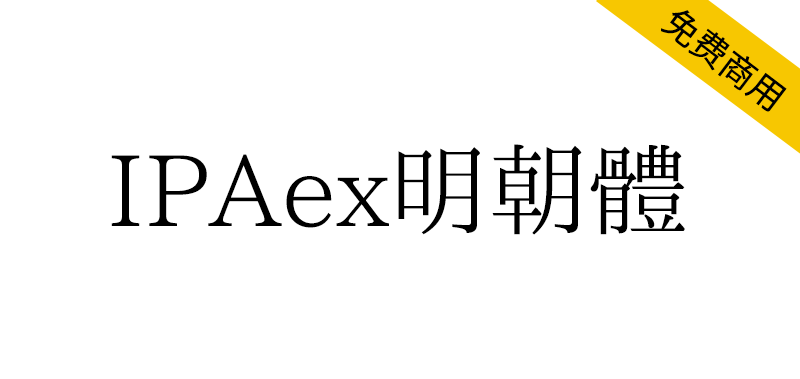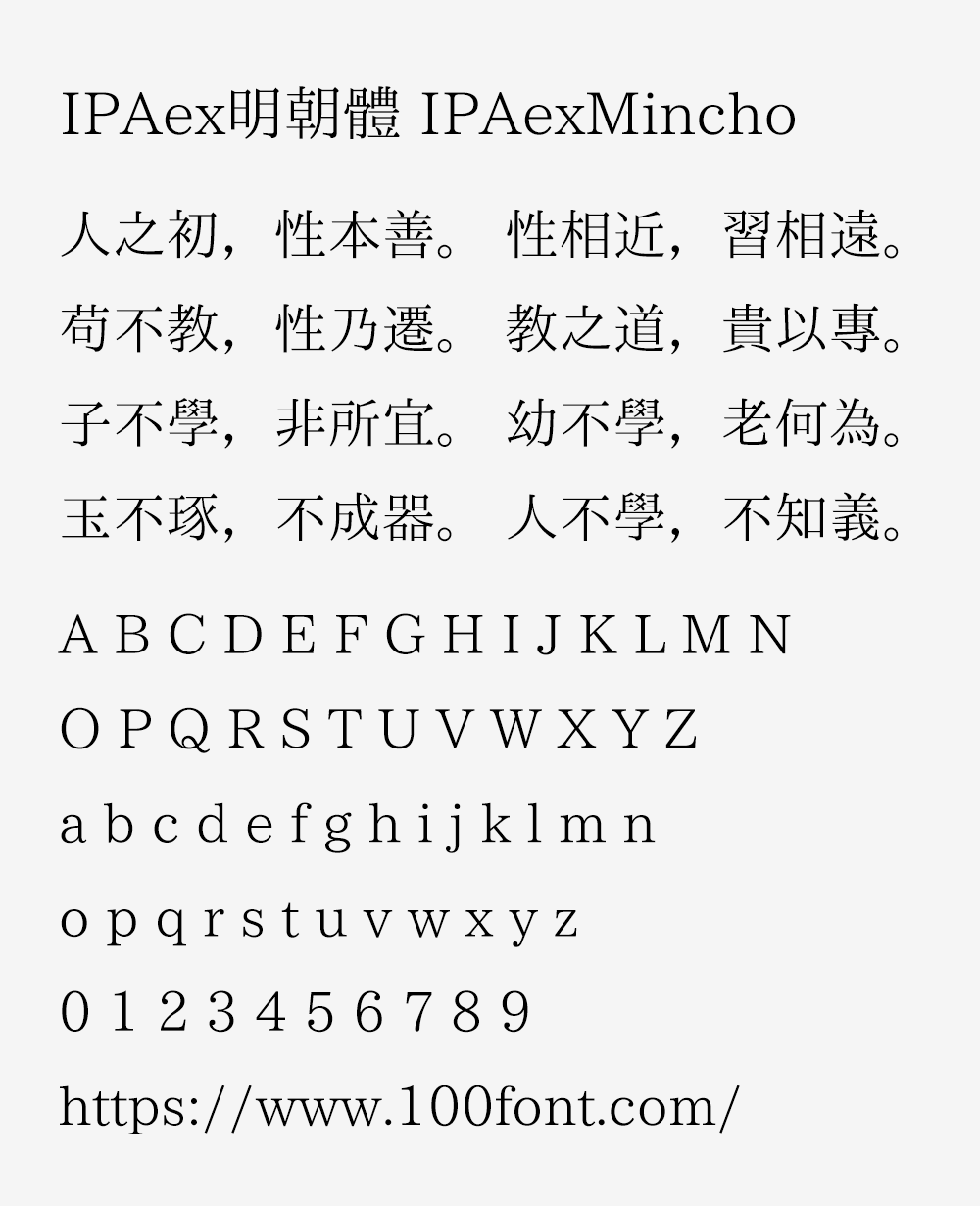
【IPAex明朝体】日本字体的标准实现文档宋体字体
揭秘日本文档背后的标准字体:IPAex明朝体如何革新日文排版体验?这款巧妙融合和文固定宽度与欧文变宽度设计的字体,以开源授权形式打破商业壁垒,获得OSI认证。无论是专业出版还是日常办公,它都能为你的日文文档注入专业品质,同时提供前所未有的使用自由。
【IPAex明朝体】日本字体的标准实现文档宋体字体
自2003年底以来,IPA一直在发布IPA拥有所有权利的“ IPA字体*”。 2010年2月,将IPAEX字体(IPAEX明朝体,IPAEX 黑体两种字体)添加到阵容中,这是日本字体的标准实现文档字体。 “ IPAEX字体”是一种旨在提高日本文档的便利性的字体,日本文字(例如Kana和Kanji)以固定宽度实现,欧洲文字是可变宽度以匹配文字宽度的可变宽度。 如果您想与过去的系统兼容,还可以使用四种类型的字体:“ IPA明朝体”和“ IPA黑体”,它们的欧洲和日本文字都具有固定宽度,以及“ IPA P 明朝体”和“ IPA P 黑体”,它们的欧洲和日本文字具有可变宽度。 “ IPAEX字体(VER.001及以后)”和“ IPA字体(Ver.003及以后)”是获得许可的“ IPA字体许可证”,这与国际实践作为开源许可证是一致的。该许可证在2009年4月1日获得OSI认证为“开源计划”(OSI)“开源定义(OSD)”。 *IPA字体是IPA的注册商标。
IPAでは2003年末よりIPAが全権利を所有する「IPAフォント*」を公開して参りました。2010年2月には、ドキュメント用日本語フォントの標準的な実装を行った「IPAexフォント(IPAex明朝、IPAexゴシックの2フォント)」をラインナップに加えました。  「IPAexフォント」は、和文文字(仮名や漢字など)は固定幅、欧文文字は文字幅に合わせた変動幅を基本とした実装を行い、日本語文書作成の利便性の向上を目指したフォントです。  なお、過去のシステムとの互換性を求める場合には、欧文文字、和文文字ともに固定幅の「IPA明朝」と「IPAゴシック」、欧文文字、和文文字ともに変動幅の「IPA P明朝」と「IPA Pゴシック」の4種類のフォントをご利用になることもできます。  「IPAexフォント(Ver.001以降)」および「IPAフォント(Ver.003以降)」には、オープンソースライセンスとしての国際的な慣習にも整合性を持つライセンス”IPAフォントライセンス”を適用します。同ライセンスは2009年4月1日に、Open Source Initiative(OSI)による「オープンソース定義(OSD)」に準拠したものとしてOSIより認定を受けております。  ※ IPAフォントは、IPAの登録商標です。